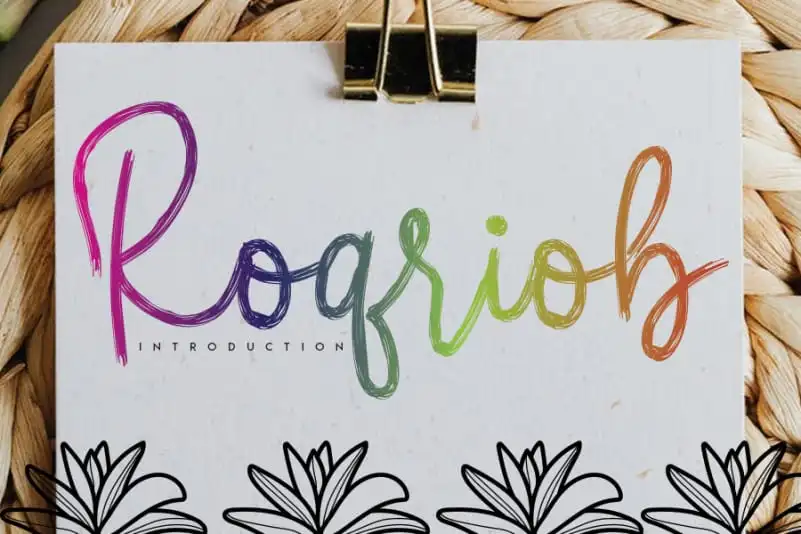
Roqriob Brush Font – Fonte Grátis
Roqriob Brush Font
Roqriob Brush Font é uma elegante fóntica que flui e traz cores vibrantes, criada com a ajuda de um pincel específico. Perfeita para quem busca se destacar e inovar em seus projetos digitais, esta fonte foi feita especialmente para criar cartões de aniversário incrivelmente bonitos, arte de estação magnífica e postagens interessantes nas redes sociais. Ela também é ideal para qualquer trabalho gráfico que exija elegância e originalidade, seja para criar lindas apresentações de trabalhos ou editoriais de moda inovadores. Descubra a beleza deste pincel único em sua próxima criação visual.